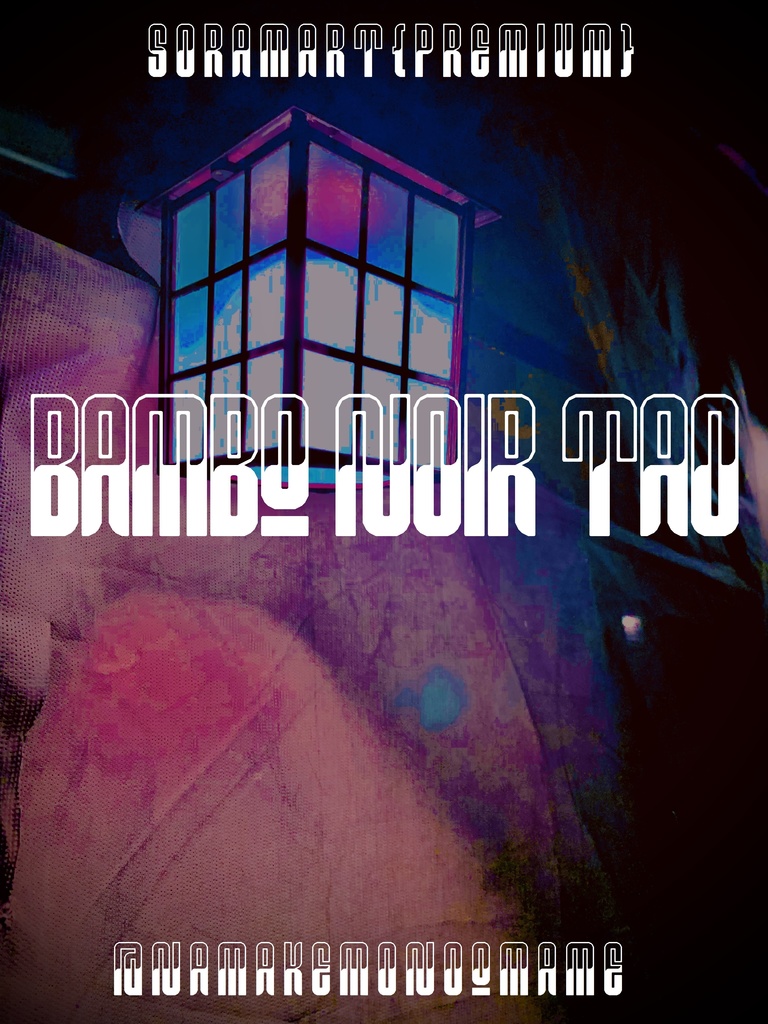
そらマートフォントデータ”Bamboo Noir Tao”Digital2,500 JPYAdd to CartBuy a GiftAbout Giftちょっと落ち着いた印象を目指した縦長シルエットフォントに白抜き加工を施した"Bamboo Noir Tao"です。 「TrueTypeフォントファイル」という形式です。 ダウンロードした後、Zipファイル内のデータをインストールしてお使いください。 このフォントは商用利用可となっております。 お客様の制作・創作活動のお役に立てれば幸いです。 ※使用上の注意事項などは、添付のReadmeをお読みください。 ※このフォントは、有料販売限定商品です。そらマートVisit FANBOX!Fontsフォントデータ”Highway Surfer Loud”そらマート2,500 JPYFontsフォントデータ”Highway Surfer Long Leg”そらマート0 JPYFontsフォントデータ”Highway Surfer”そらマート0 JPYFontsフォントデータ”Marionette Papillon Super Wide”そらマート2,500 JPYFontsフォントデータ”Marionette Papillon Wide”そらマート2,500 JPYFontsフォントデータ”Marionette Papillon”そらマート2,500 JPYFontsフォントデータ”Bolted Bonito Brick”そらマート2,500 JPYFontsフォントデータ”Bolted Bonito Bold”そらマート2,500 JPYFontsフォントデータ”Bolted Bonito”そらマート2,500 JPYFontsフォントデータ”Bit Viper UMA”そらマート2,500 JPYFontsフォントデータ”Bit Viper TUCHINOKO”そらマート2,500 JPYFontsフォントデータ”Bit Viper”そらマート2,500 JPYFontsフォントデータ”Hedgehog Serif Wide”そらマート2,500 JPYFontsフォントデータ”Hedgrhog Serif Tall”そらマート2,500 JPYFontsフォントデータ”Hedgehog Serif”そらマート2,500 JPYFontsフォントデータ”Strike Type Wire”そらマート2,500 JPYFontsフォントデータ”Strike Type Unbalanced”そらマート2,500 JPYFontsフォントデータ”Strike Type”そらマート2,500 JPYFontsフォントデータ”Bending Dummy Blank”そらマート2,500 JPYFontsフォントデータ”Bending Dummy Wide”そらマート2,500 JPYSee More